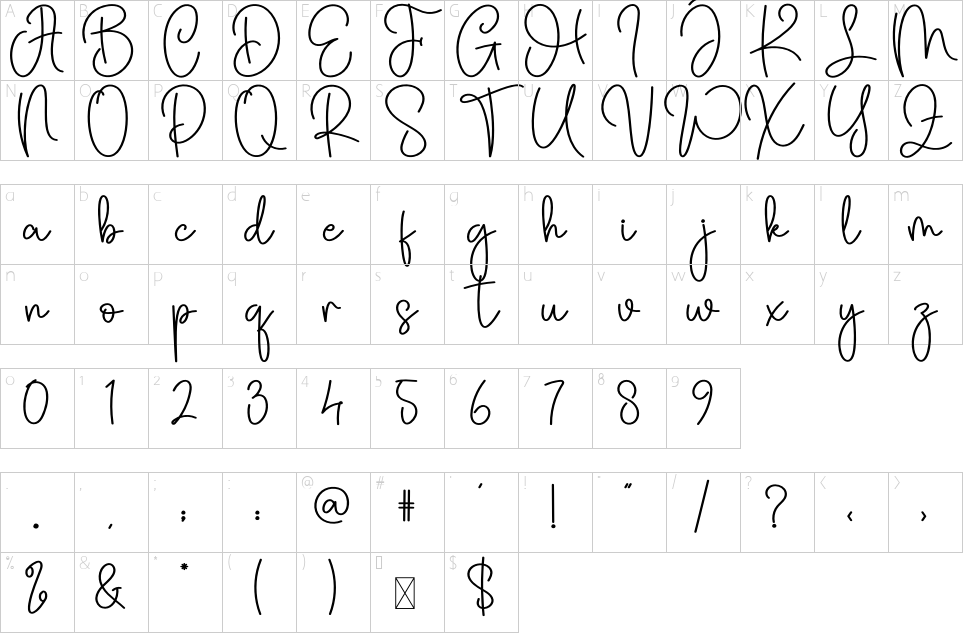
Aqui está uma descrição em português para a página de download da fonte ‘Marsmallow Font | 1001 Free Fonts’, seguindo as regras: A fonte ‘Marsmallow Font’ é uma criação da designer scratchones, um designer gráfico talentoso que nos presenteia com uma fonte gráfica e versátil. Esta fonte vem em versões para Windows e Mac, e é perfeita para qualquer projeto que busque uma aparição suave e alegre. Como seu nome sugere, a ‘Marsmallow Font’ oferece um toque de doçura e leviandade a qualquer projeto em que ela é usada. Com uma aparência agradável e fácil de ler, esta fonte é ideal tanto para aplicações digitais quanto para trabalho em papel. O designer scratchones lançou esta fonte e deu-lhe a opção de ser gratuita para uso pessoal, tornando-a uma excelente opção para designers que procuram recursos para seus projetos. Com a possibilidade de baixar esta fonte, você pode personalizar e aprimorar seus projetos gráficos de maneiras únicas, garantindo que seu trabalho seja único e cheio de vida.